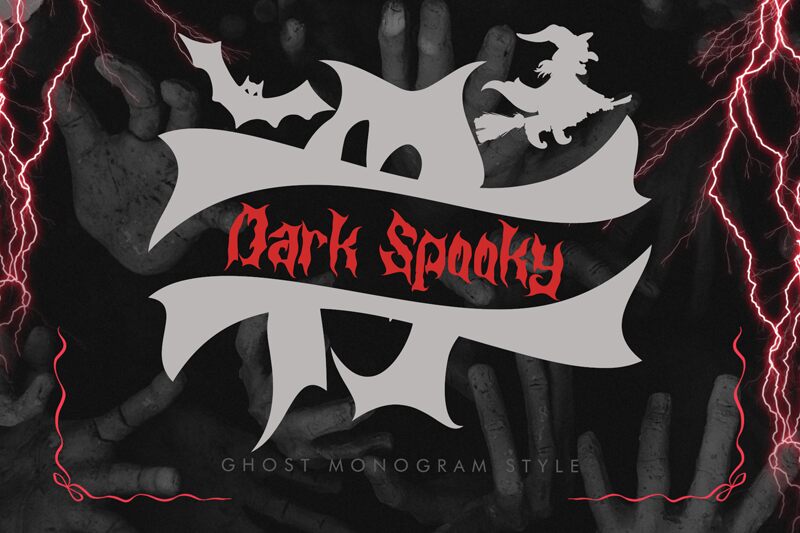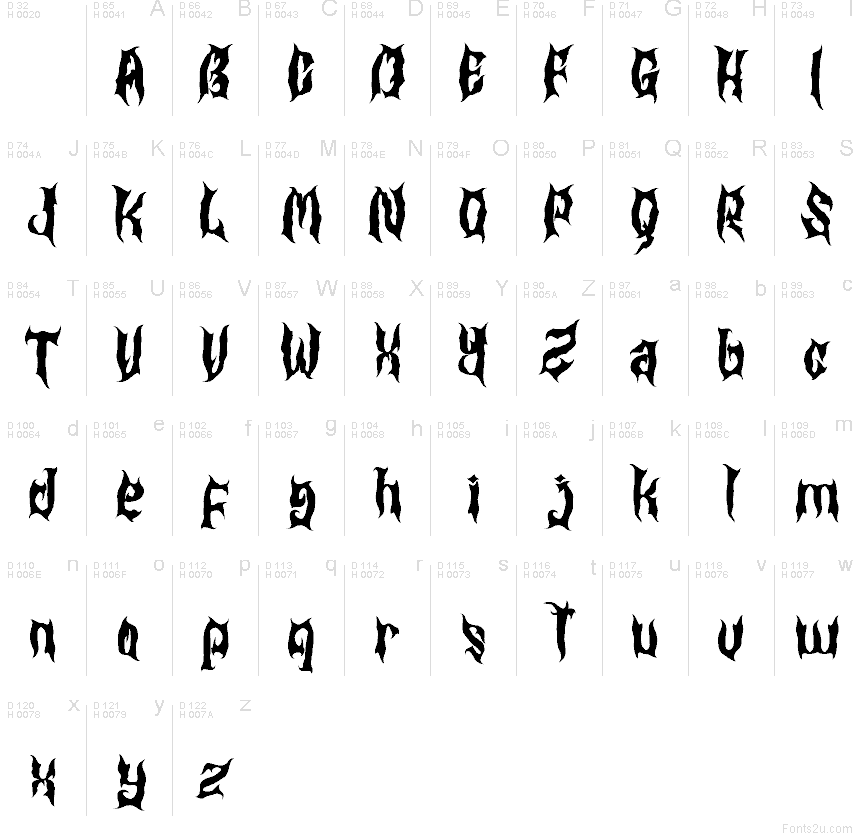
Dark Spooky Demo
Dark Spooky de Yoga Letter es una tipografía display gratuita inspirada en Halloween, con letras dentadas, deformadas y bordes afilados que le dan a cada palabra un aspecto retorcido y tallado. Sus contornos irregulares y detalles puntiagudos mantienen un ritmo áspero y siniestro sin llegar a parecer un accesorio de película de terror de serie B.
Dark Spooky funciona de maravilla en carteles de Halloween, folletos de casas encantadas, invitaciones a fiestas de disfraces, banners para eventos temáticos y logotipos, ya que su lenguaje visual fragmentado evoca inmediatamente esa atmósfera estacional. Esta fuente gratuita también es ideal para títulos decorativos, gráficos en redes sociales y textos cortos en merchandising cuando quieres que la propia tipografía haga el trabajo de dar miedo.